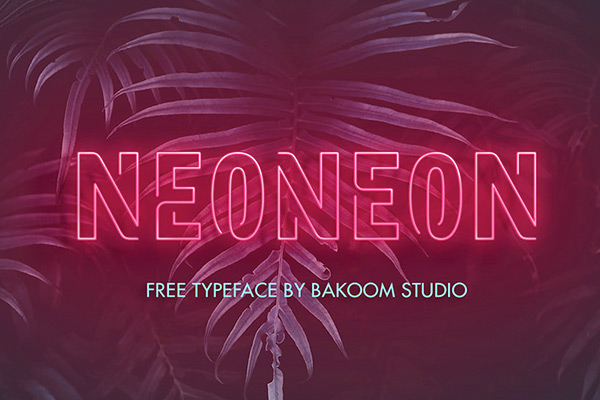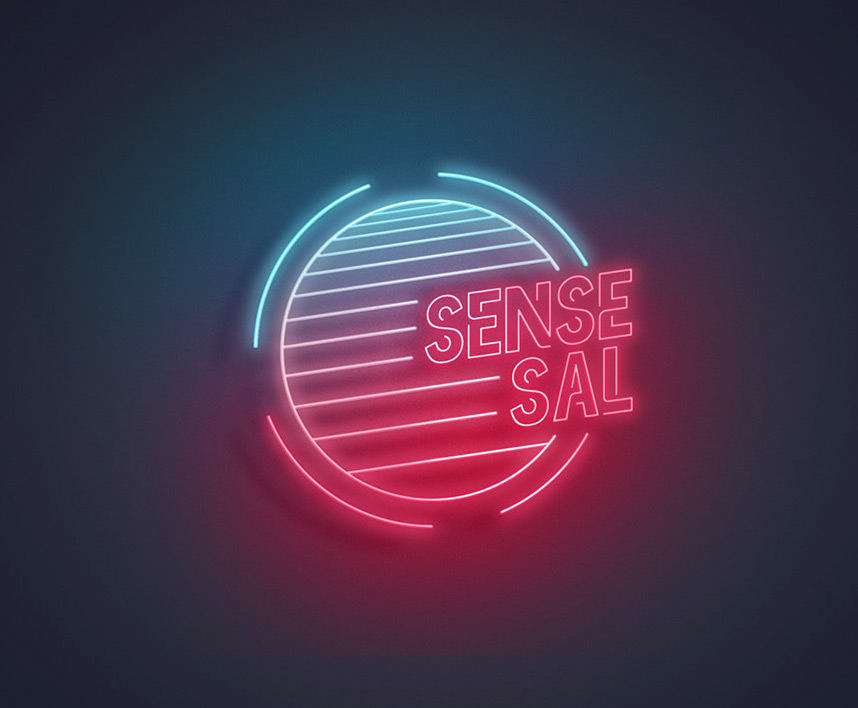
NEONEON字体
Noeoneon是一款霓虹灯风格的字体,在Photoshop中使用时能够呈现出特别发光的视觉效果。这款字体具有多用途的特点,能够模仿80年代的标牌样式,适用于广告、包装、海报设计等各种场合。
Noeoneon是由Bakoom Studio设计的第一个字体,这是一家来自西班牙的设计公司。这款字体的设计灵感来自于80年代的复古霓虹灯招牌,具有独特而时尚的外观,能够吸引人们的目光。
NEONEON效果预览